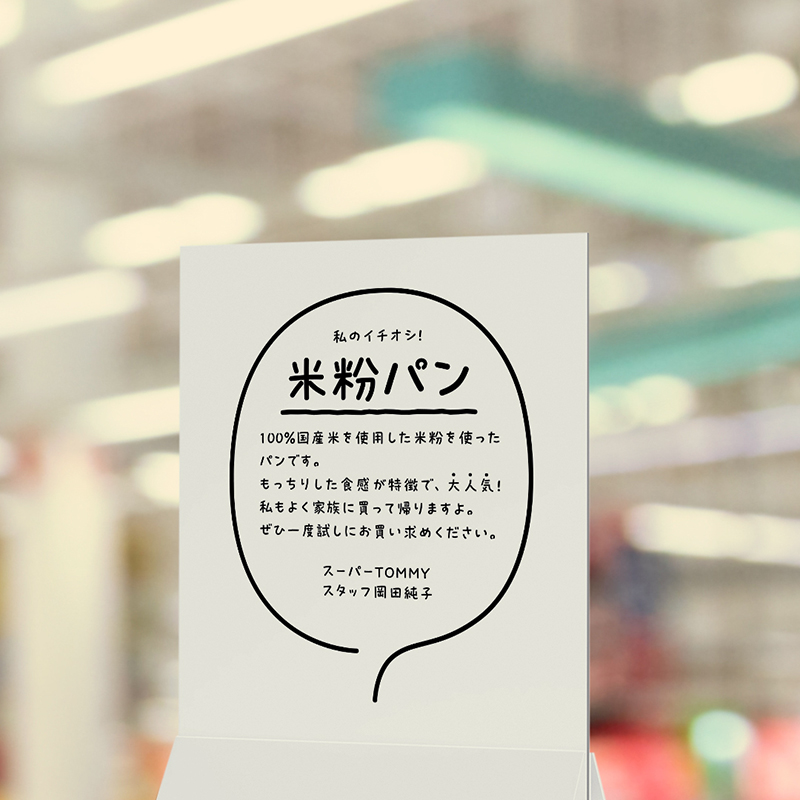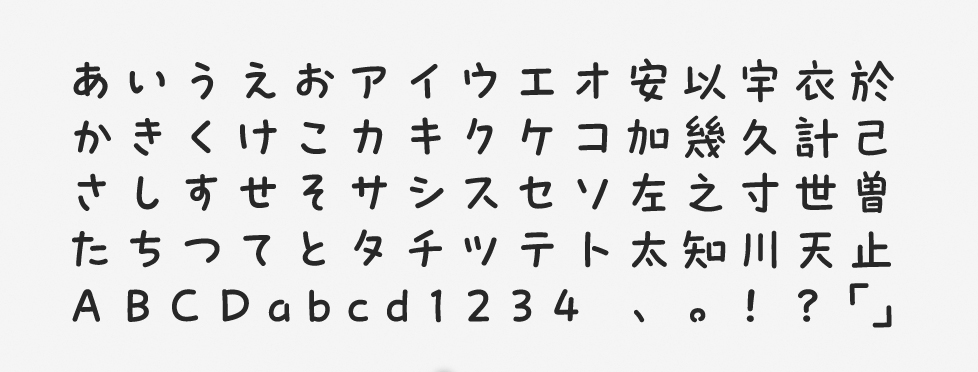
「プフ ホリデー」について
統一しすぎない自由な字形や小さめの字面を特徴とする「プフシリーズ」のフォントの1つで、2022年にリリースされました。同シリーズにはこのほかにも、プフ ポッケ、プフ マーチ、プフ ピクニックといったバリエーションがあります。プフ ホリデーは、ペンで手書きしたような明るく親しみやすいデザインのフォントです。
「プフ ホリデー」の特徴
「プフシリーズ」は楽しさや可愛さが表現されているフォント群で、その中でもプフ ホリデーはウエイトが細いペン字のようなデザインです。抑揚は弱く、しなやかな曲線で構成されています。絵本、パッケージ、コミックやチラシのキャプションなど、さまざまな場面で活用できるでしょう。
なお、「プフシリーズ」にはそれぞれオリジナルのキャラクター絵文字が1文字搭載されていて、異体字として選択入力できます。そのような “隠し要素” まで楽しめるユニークなフォントです。
作例は100%国産米を使用した米粉パンのポップで、まさにプフ ホリデーがマッチする内容です。文字と線とのシンプルな組み合わせで、ナチュラルさを強調しました。さりげない手書きのような雰囲気で、見た人に親しみを感じてもらえるでしょう。